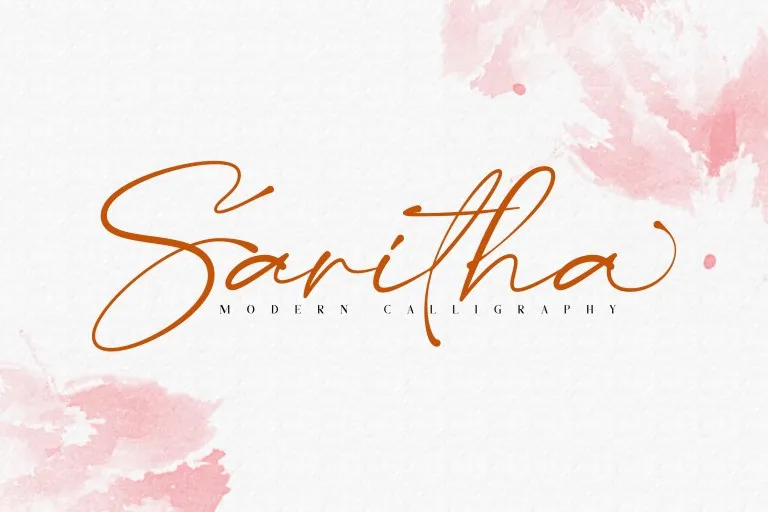
A Saritha é uma fonte de script que oferece uma harmonia tipográfica elegante para uma ampla variedade de projetos de design. Criada com cuidado e um toque romântico, a Saritha se destaca como uma opção perfeita para aplicar em designs como logos, marcações, anúncios, embalagens de produtos, publicações de revistas e até mesmo postagem nas redes sociais. Seja para criar um visual sofisticado em sua marca ou para iluminar um convite de casamento com uma elegância única, a Saritha está aqui para entregar o resultado desejado. Escolha a fonte perfeita para qualquer projeto e aproveite a expressividade única dessa tipografia delicada e impecável.